在所有的字体中,黑体和宋体基本是平时使用最多的字体,连使用率很高的圆体都是由黑体演变而来,黑体自西方而来,随着西方近代印刷术传入中国,根据西方的无衬线字体仿造的中文无衬线字体。黑体字简洁的笔画整体方正的特征与屏显介质特性相符,从而成为了当今各种屏幕媒介中发展前景的字体。今天给大家由细到粗的顺序介绍这些黑体字。
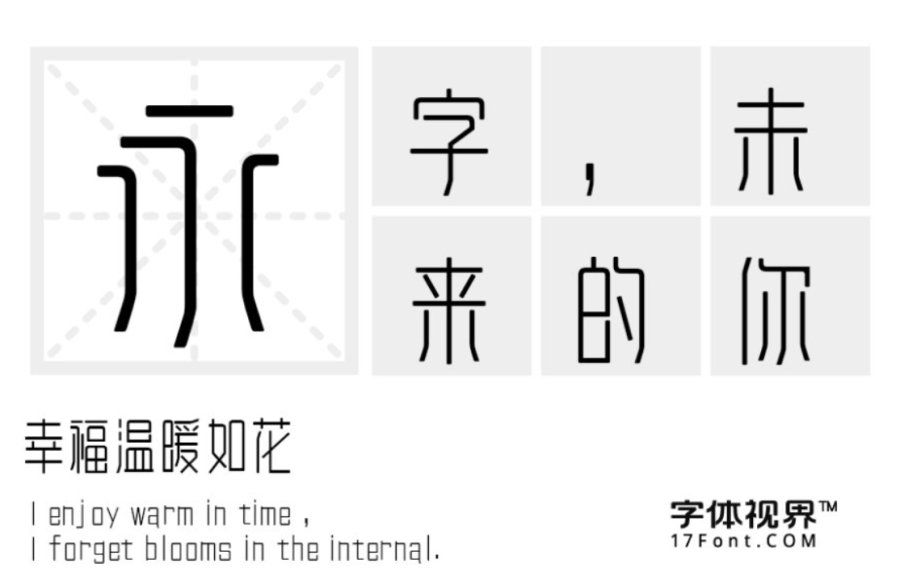
“三极雅致黑简体”是一款有着清新、文艺古典风的字体。字形清晰易于图片识别字体这款字体的字面狭长,重心较高,用笔夸张,钩、捺特点明显。笔画镜像对称,折笔统一圆弧优雅,最大简化笔画形状,简洁时尚。新颖独特、纤细流畅。整体风格典雅质朴,秀丽端正艺术性较强。适用于文艺类广告和产品包装设计。
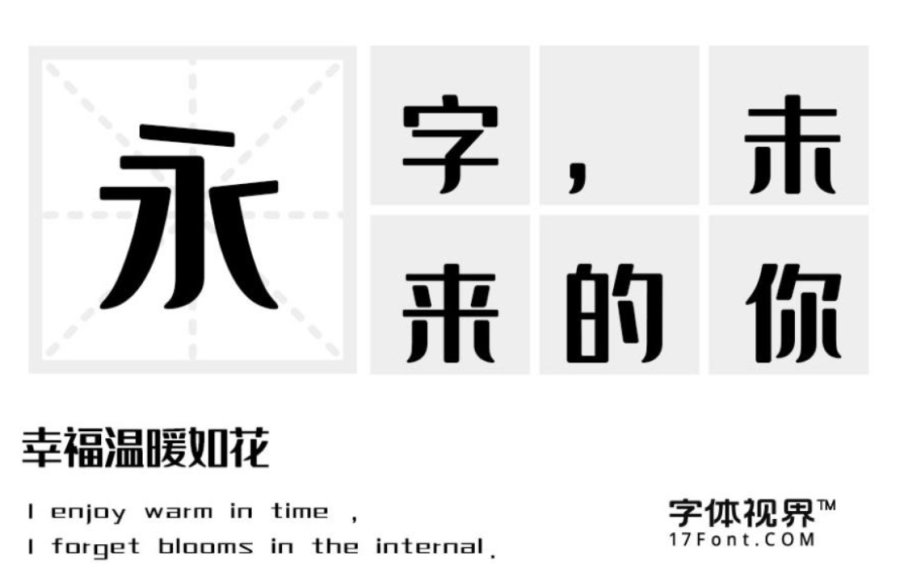
“上首润黑体”,这款字体风格方正柔丽,结构竖笔横笔都有导圆处理,竖勾做了简化处理,有的字内部进行了斜对角导圆。笔画粗壮,带有纤细笔触,字形紧聚。适用于logo设计、广告、印刷、影视等领域。
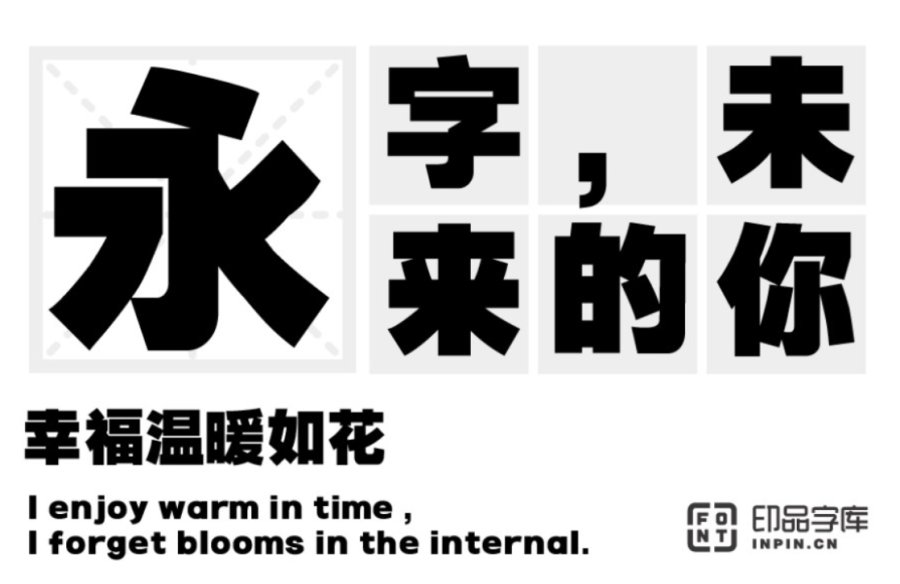
最后这一款最粗的字体叫做“印品鸿蒙体”。字体结构严谨端庄,字形饱满,字体间距布局均匀讲究 ,整体美观又大方,整体风格刚劲有力而又不失俊儒之风;笔画之中蕴含古朴沉厚端凝之势,在主标题上有很大的应用空间。
黑体字是现代汉字体系中重要的字体之一,尤其是随着20 世纪末电脑和互联网的普及 。广泛的应用在各个设计领域。在网上搜字体搜来搜去还是找不到满意的,因为黑体字层出不穷因此要选一款合适的黑体字实属不易,小编今天为大家推荐的这三款黑体字风格各异实用性高,喜欢的话就到字体视界的官网下载吧。